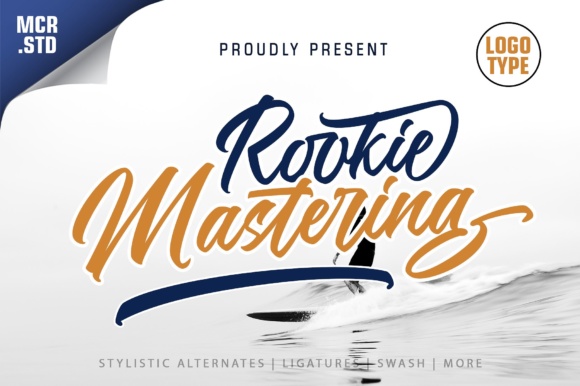
Rookie Mastering Font – احترافية التصميم تبدأ من هنا!
امنح تصاميمك لمسة جمالية مميزة مع Rookie Mastering Font، الخط العصري الذي يجمع بين الأناقة والوضوح. مثالي للمصممين، أصحاب العلامات التجارية، والمبدعين الذين يبحثون عن خط يعكس الاحترافية والتميز.
???? تصميم فريد: يجمع بين الحداثة والكلاسيكية بأسلوب متوازن.
???? استخدامات متعددة: مثالي للشعارات، العناوين، أغلفة المنتجات، والتصميمات الرقمية والمطبوعة.
???? جودة عالية: حواف نظيفة وتفاصيل دقيقة تناسب المشاريع الاحترافية.
ارفع مستوى تصاميمك واجعلها تنبض بالإبداع مع Rookie Mastering Font! ????✨